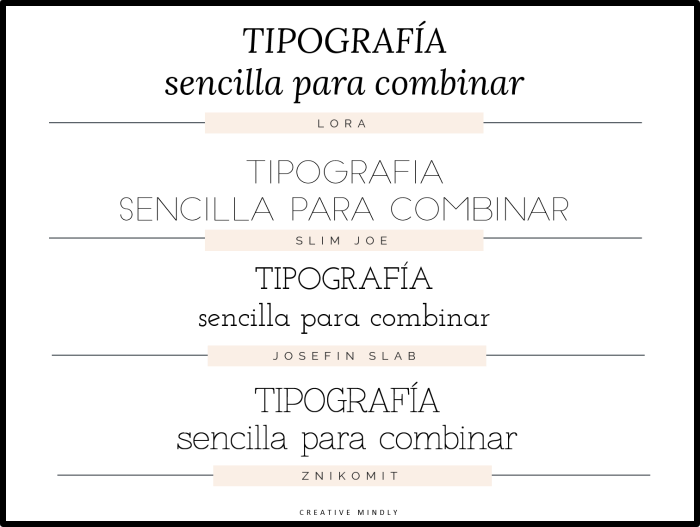
Una selección de las 16 tipografías sencillas y gratis que yo suelo utilizar para mis diseños últimamente. Sí, digo últimamente, porque soy muy cansina, y voy cambiando de tipografías por rachas. Ahora veréis que me ha dado fuerte por la Catties (que os la he dejado más abajo) pero sé que dentro de 2 meses daré por saco con otra, y seguro que también os lo diré. Total, que estas tipografías me parecen sencillas y bonitas para combinarlas con otras más especiales, con fuentes que tengan más rollo.